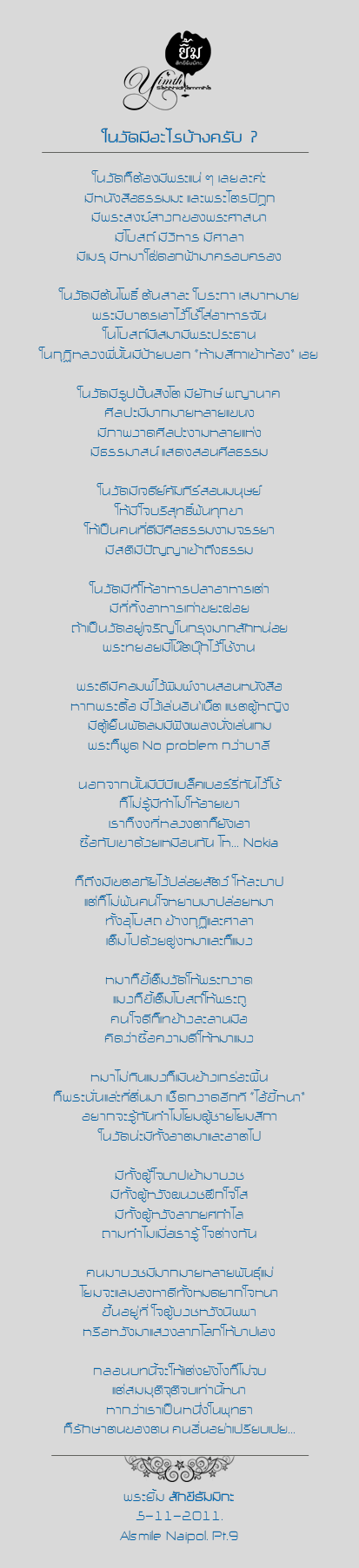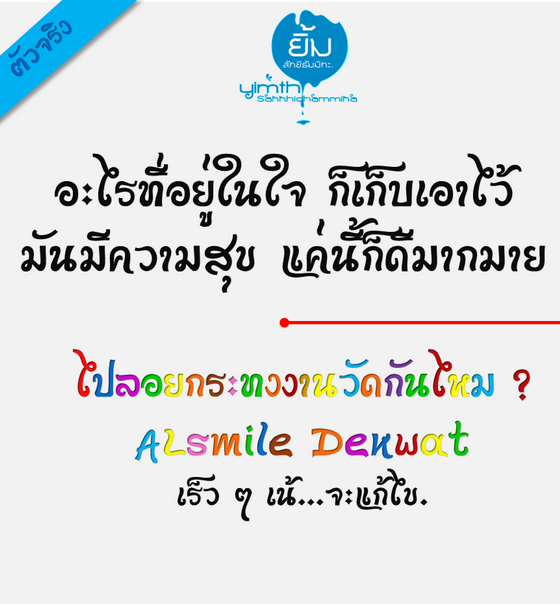
Alsmile ช่วงปิดเทอม
Alsmile ธรรมาธิปไตย์
ทำตัวไทยได้ครบแล้ว จะกรุณามากถ้าจะช่วยแนะนำ
ต้นแบบมีแค่นี้
ภาพที่หนึ่ง
ภาพที่ีสอง
ทีแรกว่าจะยึดรูปแบบเดิม แต่ทำ ๆ ไปก็เกรงจะละเมิดลิขสิทธิ์ เลยลองทำให้ต่างออกไปไม่ให้คล้ายมาก เน้นสวยเข้าไว้
อาจพัฒนาต่อไปเป็นอีกหลายรูปแบบ
ดูภาพตัวไทยก่อนนะครับ
ยังไม่สมบูรณ์แบบครับ
ข-ฃ ช-ซ มันหยักน้อยไปนิดไหมฮะ ?
สังเกตว่า ท-ฑ แอบหยักมากกว่านิดนึง
วางโดด ๆ แอบงงได้ ..มั้งฮะ
เอารวมๆ คือดูไอ้ส่วนที่ควรจะบางและควรจะหนาครับ
บางส่วนมันหนาไป อย่างร่องขยัก หรือเส้นเชื่อมระหว่างเส้นตั้ง
เซาะให้บางลงนิดแล้วจะดี
พอดีตั้งใจทำภาพรวมไว้คร่าว ๆ ก่อน
กำลังปรับครับ
ตัวนี้จำเป็นต้องทำ ตามโจทย์(ธรรมาธิปไตย์)ที่รับคำไว้
กำลังปรับให้ดูดีขึ้นในเรื่องความหนาบางและรอยหยัก ตามคำแนะนำอยู่ครับ
อันว่าตัวนายพลนี้ ปรับแล้วดูเข้าทีดี จนขี้เกียจจะชม
แต่ขมวดหัวตระกูล ผ.ผึ้ง ฝ.ฝา มันดูเหมือนใหญ่เกินชาวบ้านยังไงไม่รู้ไหมคะ
กับช่องไฟบางตัวที่มาชิดกันแล้วดูกระจุกๆ อย่างสระแอ สระเอ หรือขีดหลังขีดหน้าอะไรแบบนี้
ฟอนต์ของนายพลนี่ยังไม่ได้ปรับให้สมบูรณ์ครับ ตัวที่พิมพ์นี้ยังเป็นตัวที่เพิ่งฝึกหัดดัดปรับครั้งแรกครับ
เรื่องช่องไฟก็เลยทำตามความเข้าใจของตัวเอง ไม่ได้ใส่ใจรายละเอียดเท่าไหร่นัก ผลจึงเป็นแบบนี้
การขมวดหัวตระกูล ผ. กับ ฝ. นี่ตั้งใจทำให้มันเด่นครับ คิดว่าชอบแบบนี้ มันอาจดูใหญ่เกินชาวบ้าน แต่เจตนาครับ
ไม่อยากให้ถูกถามว่าจะงงกับตัว พ. ฟ. ไหม เลยตัดสินใจทำ พอทำแล้วนึกชอบก็เลยไว้ลายแบบนี้ละครับ